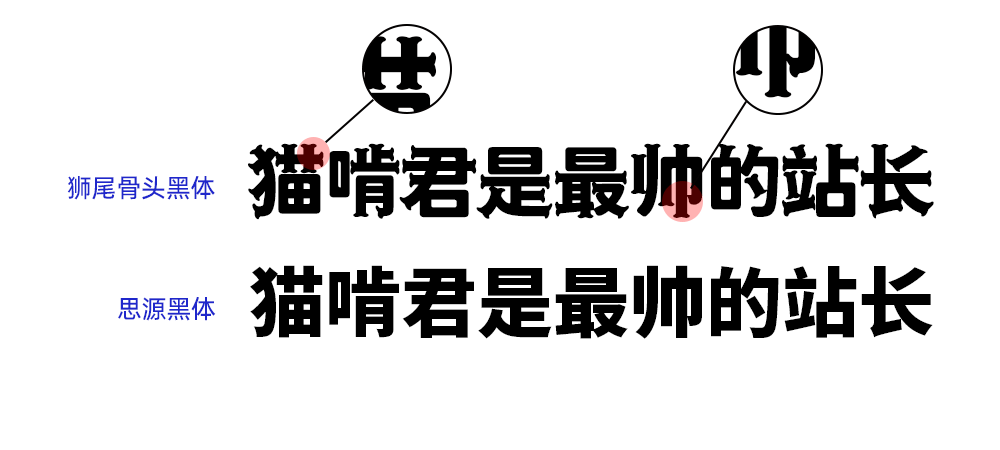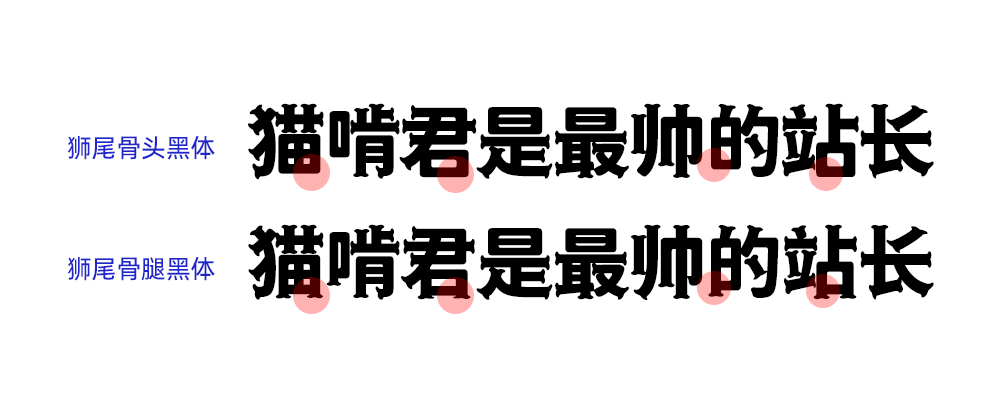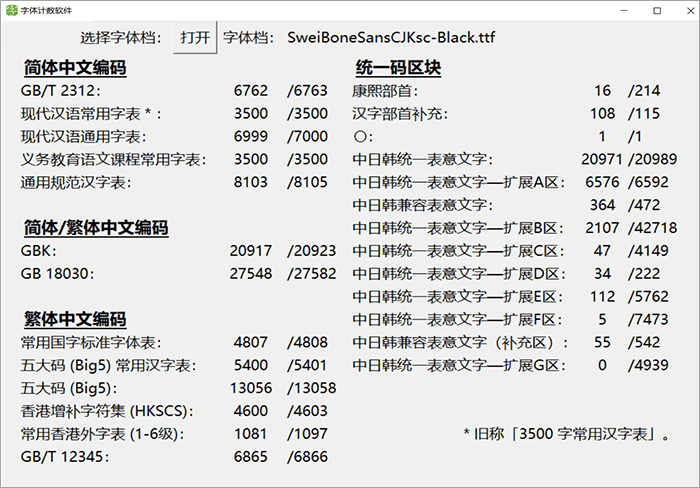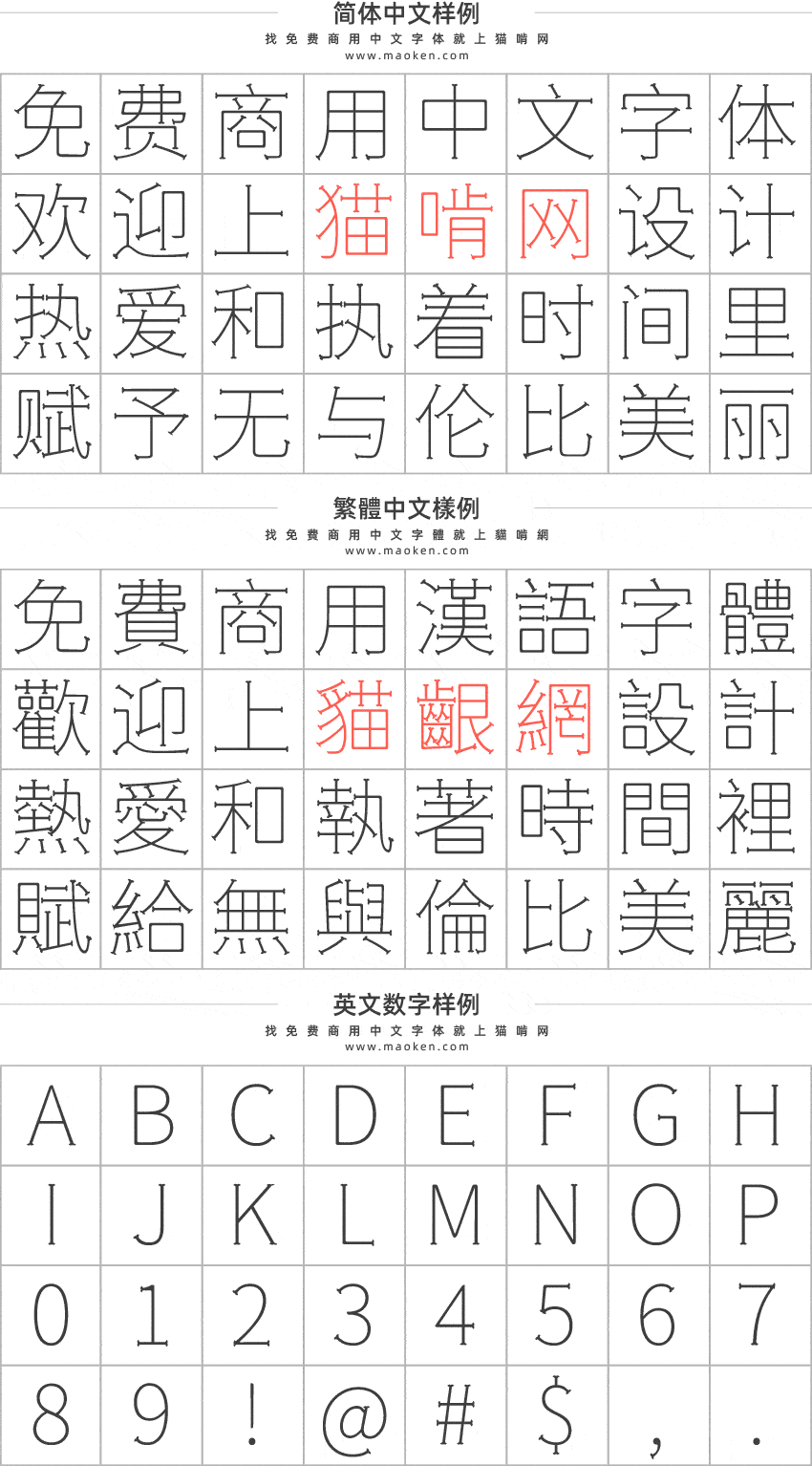
狮尾骨头黑体基于思源黑体的笔触变骨头和拔脚改造,更加简明现代化的字体。支援简体中文、繁体中文、韩文与日文;可以免费商用,欢迎大家自由应用、自由优化、自由改作!下面是狮尾骨头黑体与思源思体的对比效果图。
Max发布的字体一般包括两个版本,就是狮尾骨头黑体和狮尾骨腿黑体。这两款字体的最主要区别是有脚和没有脚的区别。有拔脚的字会较圆,但是会造成有些字因直接去掉腿后左右不平衡、左右不对衬的「悬空」问题。改使用「腿」系列字体就不会有这个问题。